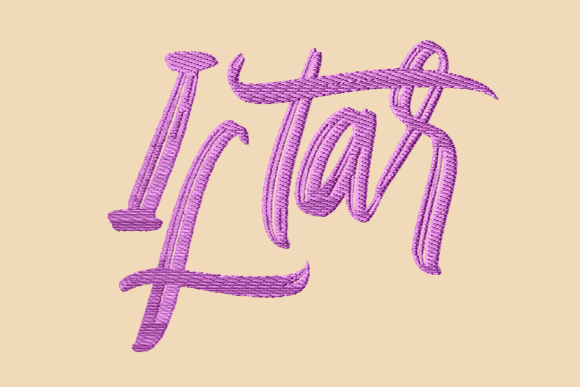
Iftar Lettering Script
์˜ฌ๋ฐ”๋ฅธ ๋””์ž์ธ ์š”์†Œ๋ฅผ ์ฐพ๋Š” ๊ฒƒ์€ ์–ด๋ ค์šธ ์ˆ˜ ์žˆ์ง€๋งŒ Iftar Lettering Script๋Š” ์ž‘์—…์„ ์ฆ‰์‹œ ํ–ฅ์ƒ์‹œํ‚ค๋Š” ๋›ฐ์–ด๋‚œ ์ปฌ๋ ‰์…˜์„ ์ œ๊ณตํ•ฉ๋‹ˆ๋‹ค.
์ •๋ฐ€ํ•˜๊ฒŒ ์ œ์ž‘๋œ Iftar Lettering Script๋Š” ๊น”๋”ํ•œ ๋ฒกํ„ฐ, ๋ถ€๋“œ๋Ÿฌ์šด ํƒ€์ดํฌ๊ทธ๋ž˜ํ”ผ ๋ฐ ์•ˆ์‹ฌํ•  ์ˆ˜ ์žˆ๋Š” ์ƒ์—…์šฉ ๋ผ์ด์„ ์Šค๋ฅผ ์ œ๊ณตํ•ฉ๋‹ˆ๋‹ค.
POD(์ฃผ๋ฌธํ˜• ์ธ์‡„) ์ œํ’ˆ, ๊ฒฐํ˜ผ์‹ ์ดˆ๋Œ€์žฅ ๋˜๋Š” ์†Œ์…œ ๋ฏธ๋””์–ด ๊ทธ๋ž˜ํ”ฝ์„ ๋งŒ๋“ค ๋•Œ Iftar Lettering Script๋Š” ์ด์ƒ์ ์ธ ์„ ํƒ์ž…๋‹ˆ๋‹ค.